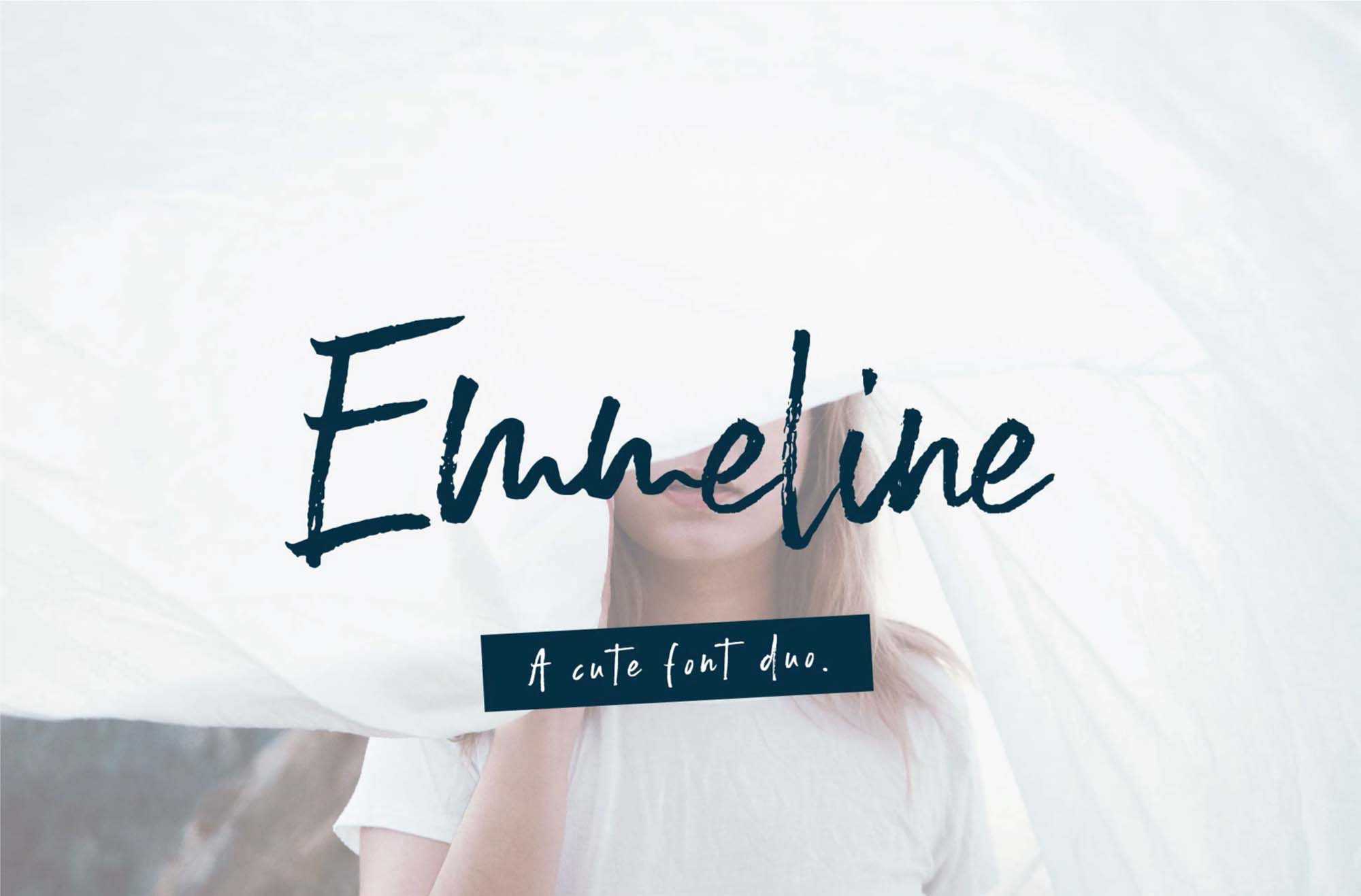
Emmeline Free Brush Font – Download Grátis
Emmeline Free Brush Font
A Emmeline Free Brush Font é um recurso gráfico que remete às influências de uma das mais respeitadas e revolucionárias técnicas de pintura: os pinceladas. Ao explorar sua riqueza e variedade, você invoca a arte das pinturas de nomes consagrados como Claude Monet, Van Gogh e Edouard Manet. Essa fonte em formato de pincel abrange uma ampla gama de estilos e técnicas que, inspiradas nos estilos de cada pintor, fornecem a oportunidade de criar ambientes artísticos vibrantes e emocionantes. Embora a Emmeline Free Brush Font possa ser utilizada para qualquer aplicação visual, desde logotipos até trabalhos gráficos em geral, ela é particularmente útil para criar ambientes que remetem à pintura e à arte do pincel. Ela captura a essência de cada pintor e transforma essas técnicas em formas visuais que podem ser manipuladas e adaptadas de várias maneiras. É mais do que uma fonte; é uma conexão com a arte que permeia todas as obras de arte, tornando a Emmeline Free Brush Font uma ferramenta poderosa para qualquer designer que deseja explorar a poética da pintura através do design de gráficos.